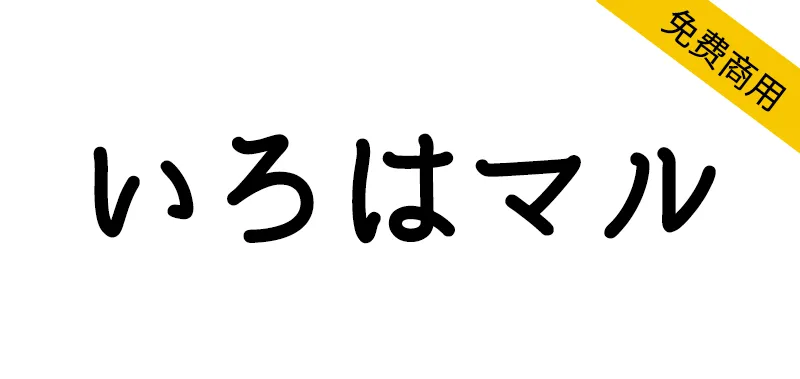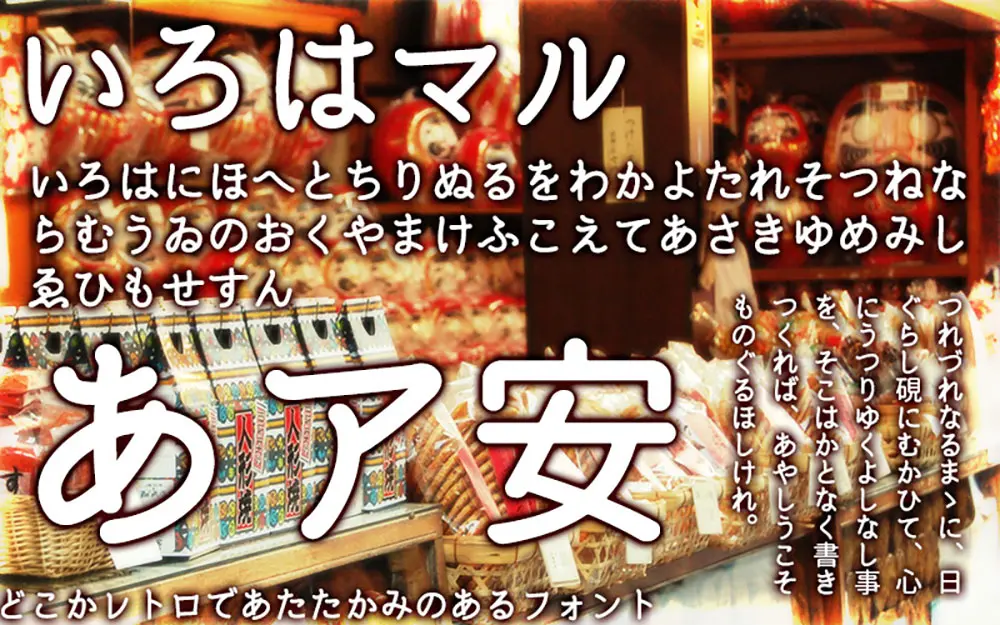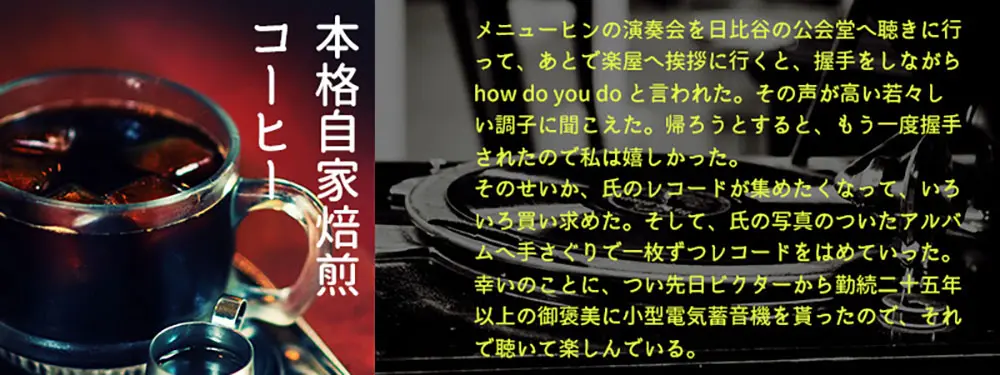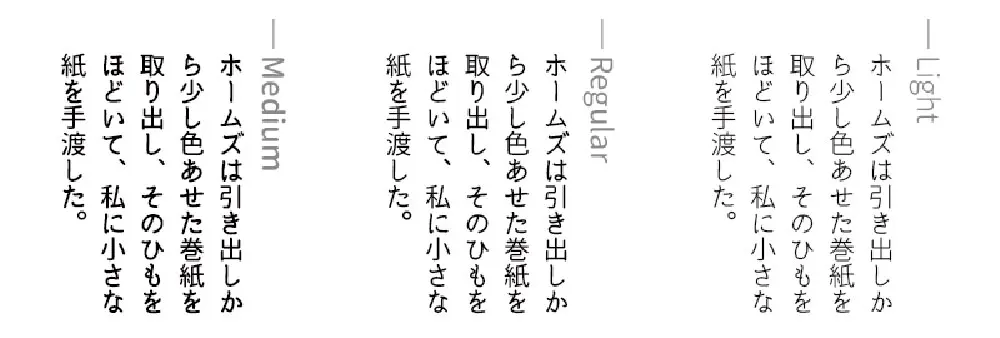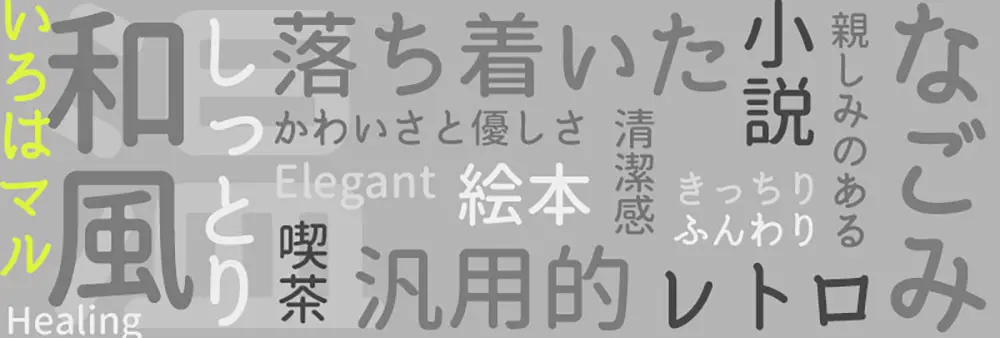
いろはマル(irohamaru)是一款基於思源柔黑體的衍生字體,並具有原始的平假名,片假名和一些其他符號。它是一種易於使用的字體,具有圓形哥特式的感覺,但又有點復古的感覺。如果你仔細觀察,你會發現平假名和片假名柔軟而寬鬆,給人一種味道和溫暖的感覺。
源ノ角ゴシックの派生フォントである『源柔ゴシック(自家製フォント工房/MM様)』の漢字を用い、ひらがな・カタカナ・その他一部記號をオリジナルにした改変フォントです。丸ゴシックながらどことなくレトロ感の漂う、使い勝手の良いフォントです。よく見るとひらがな・カタカナは、ふにゃっとしていたり、ガタつきがあったり、味とあたたかみとして効果になっているんじゃないかと思います。